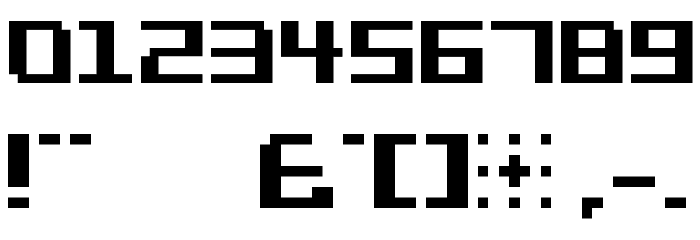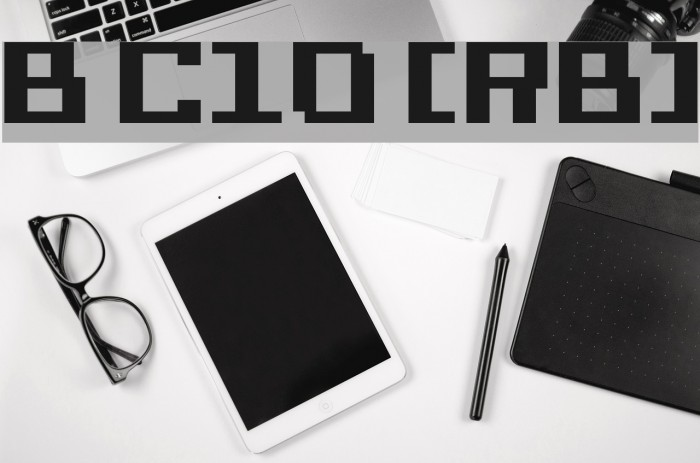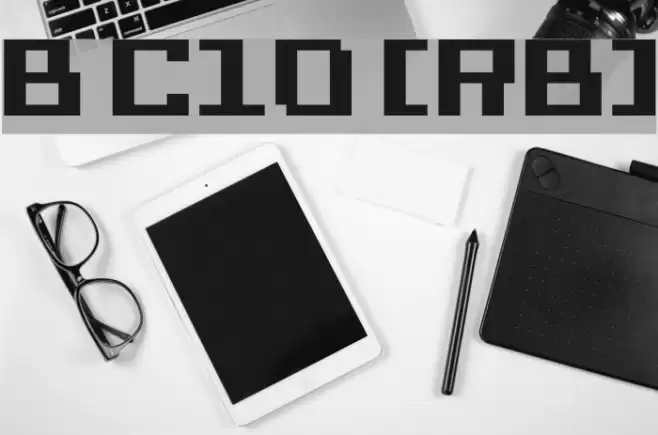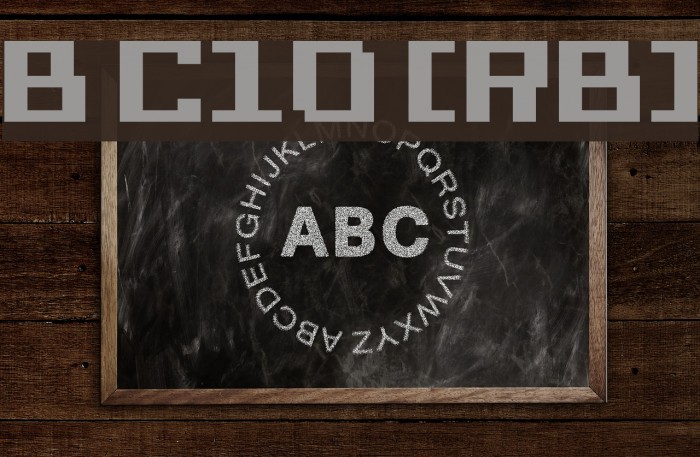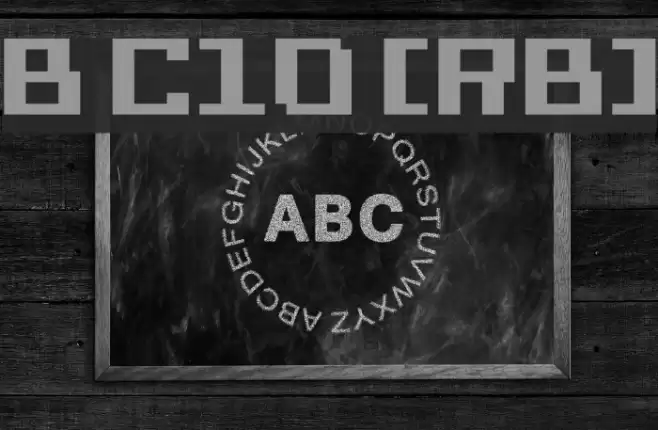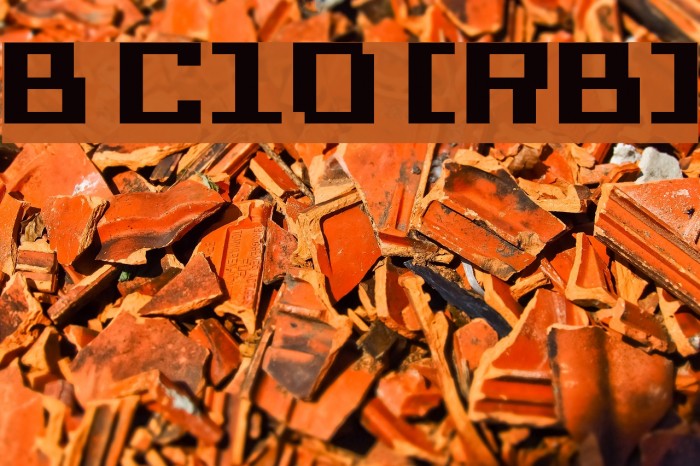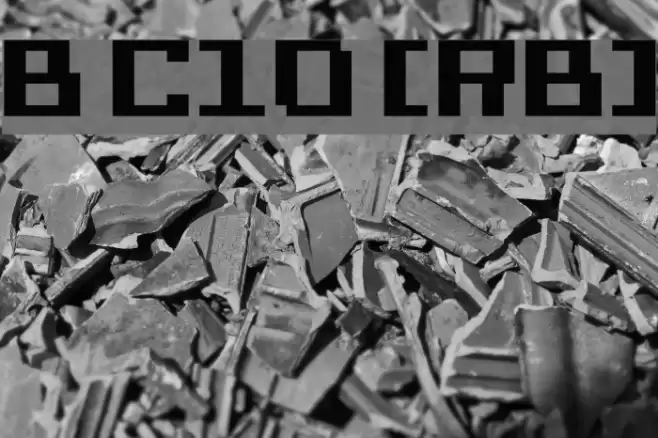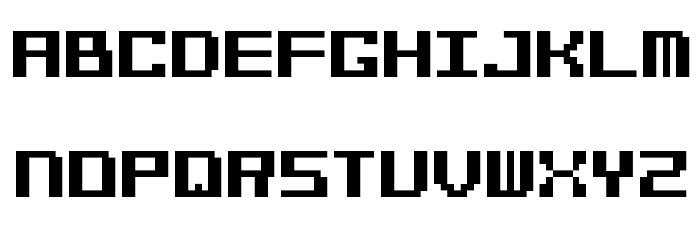
Bit Cheese10 [sRB] Font
| Estilo geral | Retro, Digital |
| Caso de uso | Headlines, Logos, Digital Art |
| Projetos propostos | Ideal for video game design, retro-themed posters, digital art, and tech-related branding. |